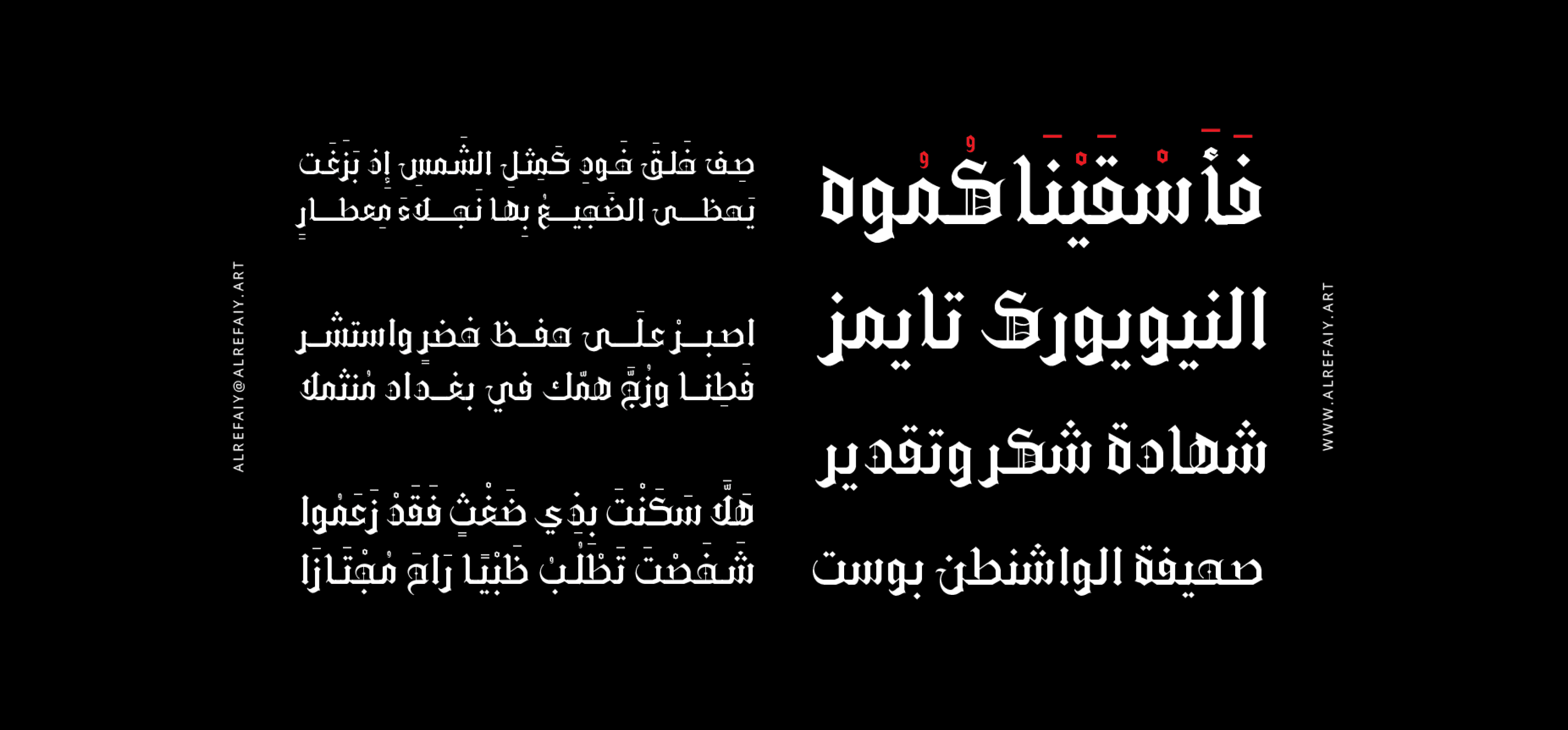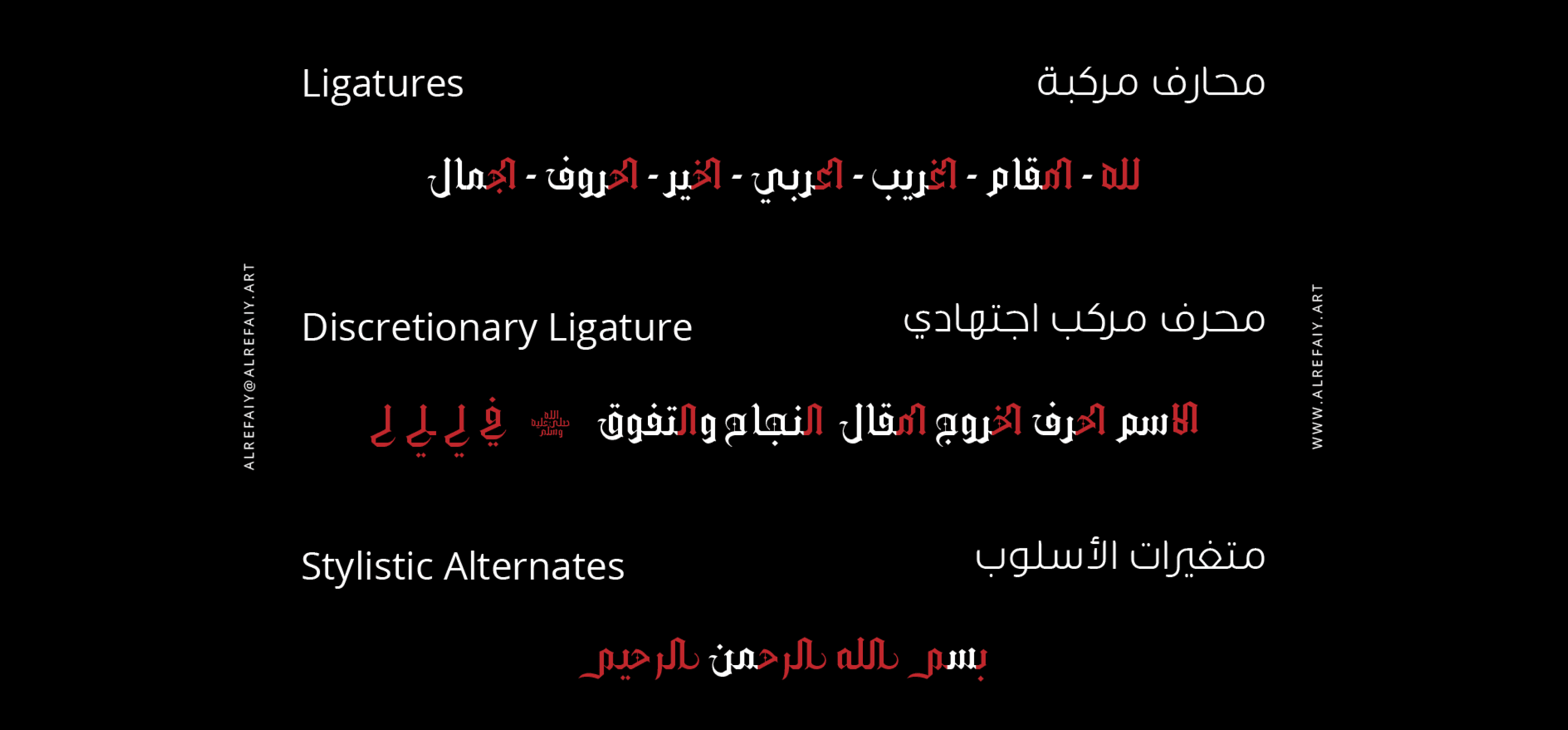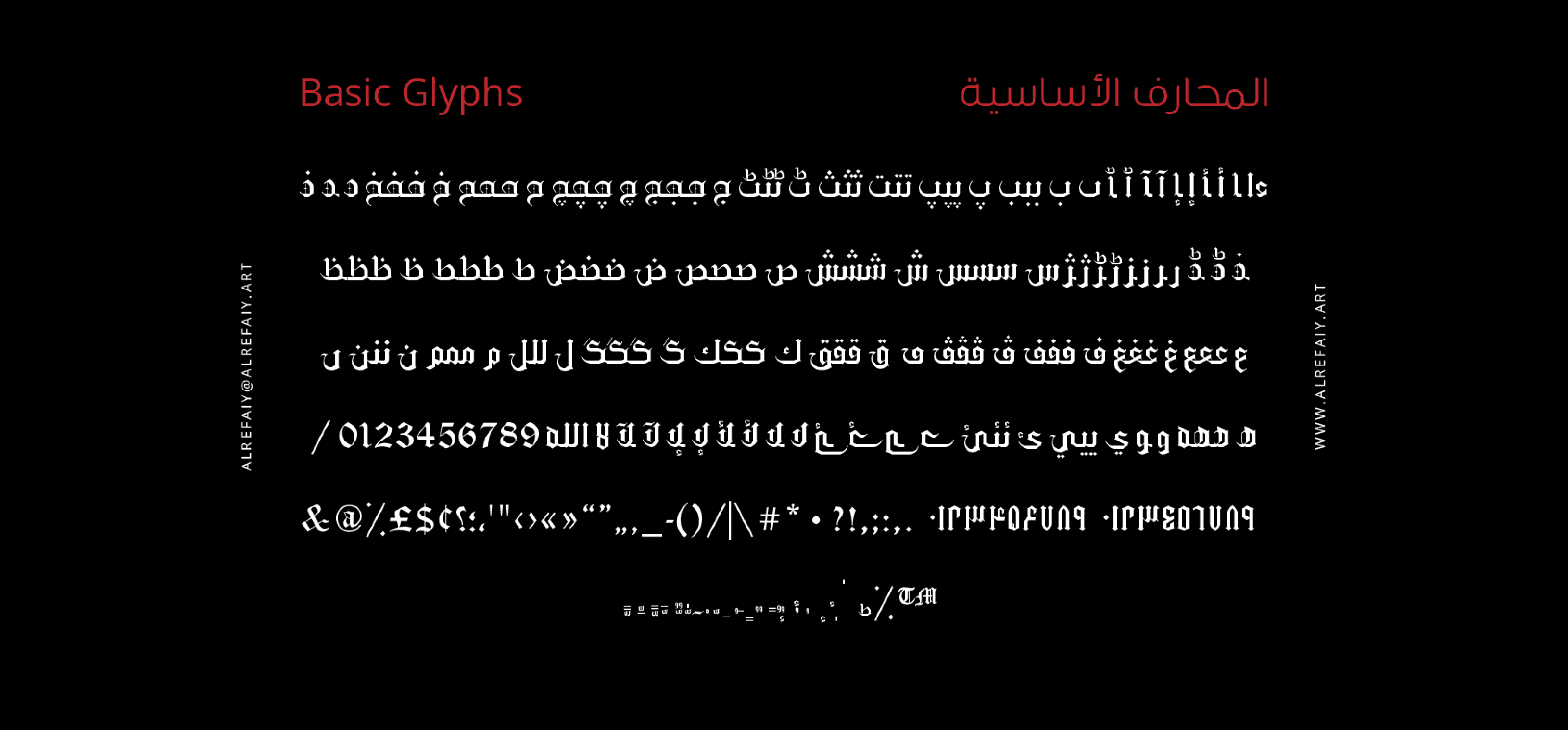
خط YR Gothic Arabic مستوحى من الأسلوب الخطّي القوطي المعروف بأناقته الكلاسيكية الخالدة. يتميز هذا النمط بتوازن متناغم بين السماكات الغليظة والرقيقة، مع تركيز واضح على الخطوط الرأسية، ما يمنح الخط حضورًا قويًا ومظهرًا مميزًا يجمع بين الفخامة والدقة.